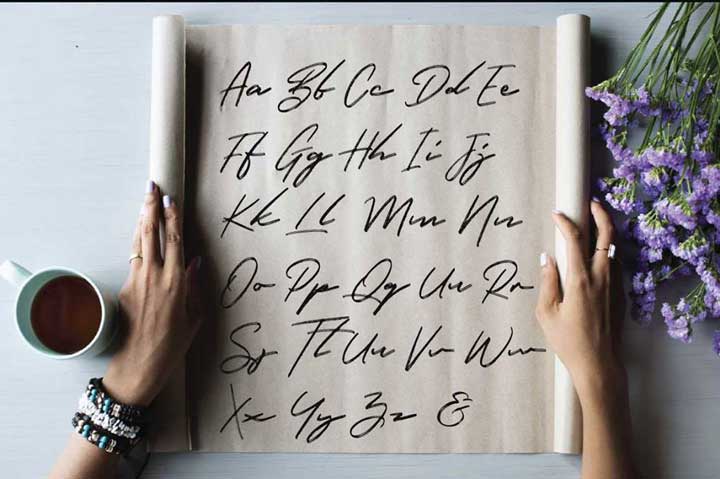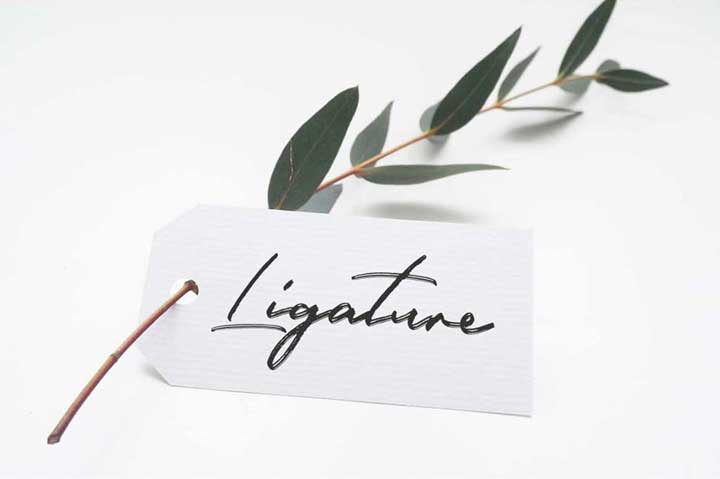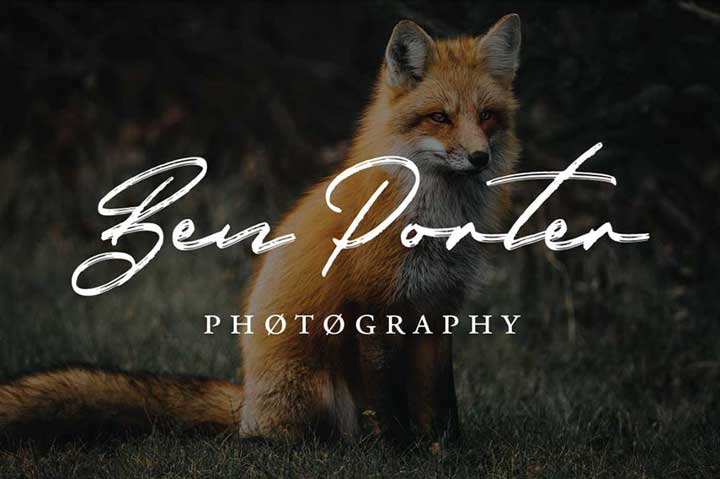
Hunter River Free Signature Script Font
Hunter River adalah font tulisan tangan /Signature Font karya Hustle Supply Co. yang dirancang untuk memberikan kesan klasik dan tradisional dalam berbagai desain. Font ini sangat cocok digunakan untuk judul atau title pada kartu, postcards, kemasan produk (packaging), label, pakaian (apparel), cetakan (prints), kutipan (quotes), dan media lainnya yang membutuhkan sentuhan elegan dan vintage.
Karakteristik Unik Hunter River:
• Tampilan Tulisan Tangan: Hunter River meniru gaya penulisan tangan dengan goresan yang natural dan mengalir.
• Kesan Klasik dan Tradisional: Font ini memberikan nuansa vintage yang cocok untuk desain bertema retro, rustic, atau elegan klasik.
• Versatilitas: Hunter River dapat digunakan untuk berbagai media, mulai dari desain grafis hingga teks pada produk fisik.
Contoh Penggunaan Hunter River:
1. Kartu Undangan: Gunakan Hunter River untuk judul kartu undangan pernikahan atau pesta dengan tema klasik.
2. Desain Kemasan: Berikan sentuhan elegan pada kemasan produk makanan, minuman, atau kerajinan tangan dengan menggunakan Hunter River sebagai font utama.
3. Label Produk: Buat label yang menarik dan informatif dengan menggunakan Hunter River untuk nama produk dan informasi penting lainnya.
4. Kutipan Inspiratif: Tampilkan kutipan inspiratif dengan gaya yang unik dan memikat menggunakan font Hunter River.
5. Cetakan Seni: Hunter River dapat digunakan sebagai font utama pada cetakan seni atau poster bertema vintage.
Dengan karakteristiknya yang unik, Hunter River Signature Font menjadi pilihan tepat untuk desainer yang ingin menambahkan sentuhan klasik dan elegan pada karya mereka. Font ini tersedia secara gratis dan mudah diunduh, sehingga dapat digunakan oleh siapa saja tanpa biaya.